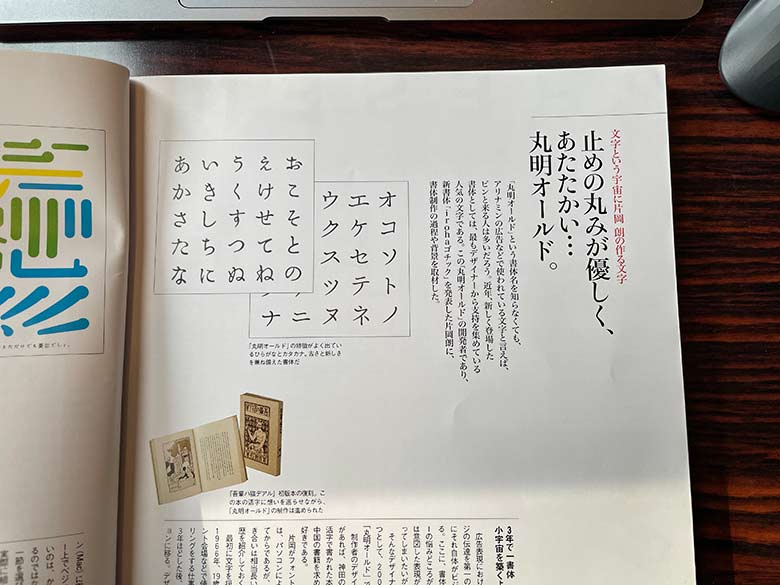
2021年衝撃のニュースでした
あの丸明オールドと、そのシリーズがAdobeフォントで使えるようになったと!
- 丸明オールドのすごさ
- 使いみち
- 今までみんなが代わりに使っていた似たフリーフォント
などなど紹介していきます
丸明オールドを制作しているのは砧書体制作所(旧:カタオカデザインワークス)です。
丸明オールドのすごさ
丸明オールドは一世を風靡したフォントです。
発売は2001年、その頃たくさんのCMや広告で使われました
丸明オールドの印象を一言で言うこんな感じかな
懐かしいけど古すぎない、かしこまってるけど、堅すぎない
使用例を見てもらうとわかるかと思います
丸明オールドの使用例
イラストレーター上でそのまま丸明オールドで打つとこんな感じになります
その他、ケンタッキー、ローソン、ファミレスなどで、今でもめちゃくちゃ使われています。
あ、これもそうです、セブンイレブンのコーヒー
カタカナ部分がちょっと太くした丸明オールドですね。
丸明オールドは”長い歴史のある明朝体の新しい風”
販売サイトにはこう書いています
懐かしくて、モダンな明朝体。筆文字のような形のかなが特徴です。
漢字とかなの大きさのバランスが違いますが、不思議と縦に組んでも横に組んでもきれいで読みやすい。漢字は縦線、横線、点、トメ、ハネ、ハライなどどれも先端が丸くなっています。長い歴史のある明朝体の新しい風として話題になった書体です。
長い歴史のある明朝体の新しい風 だったんです。
流行り具合でいうと、今で言うキリギリスやオールド系のA1明朝、A1ゴシックというイメージです。
僕もとにかく憧れました
多分、みなさんも間接的に馴染みがあるとフォントだと思うんです。
それはなぜかと言うと
丸明オールドに似ためちゃくちゃヒットフリーフォントがあるんです
それが・・・
はんなり明朝という伝説
はんなり明朝はフリーフォントです。
みんな知ってますよね?
はんなり明朝はデザイナーじゃなくても会社でデザイン的なことをやるときに一度はダウロードしたことあるフォントだと思います。
これも懐かしくて使いやすいフォントでした。
最近すっかり使いみちは減りましたが、和風を表現するときなど未だに使うこともあります。
はんなり明朝も 「筆!」という主張がしすぎないけど、和風な使いやすいフォントです
ただ、はんなり明朝ってさ、知ってます?
ひらがな、かたかな だけがオリジナルで、漢字は普通の明朝体なんです
漢字はIPA明朝体というものなんです。
でもめちゃくちゃ雰囲気出たフォントですよね。天才が作ってる。
ちなみに、はんなり明朝のサイトにはこう書かれています
やさしくて、ふんわりとした、ひらがなとカタカナをデザインしています。
漢字と英数字、記号などはIPA明朝体で補っています。
はんなり明朝と丸明オールドの比較してみます
漢字+ひらがな
ひらがなのみ
▼漢字のみ
よくみるとぜんぜん違うんですけどね
イメージとしては同じように使えると思います。
デザイナーってフォントのことこうやって考えてると思うんです。
- はんなり明朝は、普通の明朝体よりちょっとやわらかい
- はんなり明朝は、筆文字より普段着的に使える
みたいな、相対的な感覚で考えていると思うんです。
僕が押している「相対的フォント感」という考えですがいかがでしょうか?(絶対的にフォントを当てられなくても、イメージで覚えていればOKかなと)
その考え方でいうと、はんなり明朝と丸明オールドって同じような位置にいるフォントだと僕は思います。
丸明オールドの使い方事例(名刺だよ)
では、最後に丸明オールドはどうやって使うのか、事例をやってみます。
前に仕事ではんなり明朝を使って作った事例があるので見ていただきましょう
米の農家さんの名刺です
背景のテクスチャも和を感じさせるデザインです。
これが筆文字だと・・・ほら主張が強すぎない?
江戸時代から米しか作ってないでっせ!しかも機械はもってないでっせ!というイメージの農家の名刺になっちゃいます。
高級料亭じゃないけど、上品な和の雰囲気を出しつつ、硬くなりすぎない和のデザインを作れるのが丸明オールドかなと僕は思っています。
高尚すぎない自然感って言うんですかね。
もちろんこれは一つの事例、和じゃなくても使いみちはありますね。
まとめ すごいことが起きてる
2001年発売のフォントなので、僕も丸明オールドのがっちり世代でもないんです。
だけど、当時このフォントが新しい風を起こしていた空気は感じていました
ちなみにね、丸明オールドを作っている砧書体制作所(旧:カタオカデザインワークス)の他のフォントもAdobeフォントで使えるようになりました
一時代を築いたクオリティのフォントを「試しに使ってみる」ことができるなんて最高の時代ですね。
最後に
僕の中ではAdobeフォントで、貂明朝を知ったときくらいの衝撃です。それ以上かな。
でも貂明朝うまく仕事で使えたことないんだけどね…
そして最後に販売サイトから引用、「伝説感」強くて楽しくない?
直線を意識しつつも丸いエレメントを多用した漢字と毛筆の運びを強く感じる仮名が特徴的で確かな個性を発揮する「丸明オールド」。2000年に発表されて以来、数多くのアートディレクター、デザイナーに愛され続け、CM、広告、Webなどの様々なシーンで使用されています
2000年2月に掲載された新聞広告、サントリーモルツの広告キャンペーンで鮮烈なデビューを遂げた「丸明オールド」。それまでにはなかった丸明朝体というカテゴリーを作ったこと、また発売前のフォントが世の中に登場したということもあり話題の書体となりました。
砧書体制作所(旧:カタオカデザインワークス)の他のフォントも楽しそうだなあ
おまけ
古本で買ったデザインノートに丸明オールドの特集があって盛り上がったのを覚えている